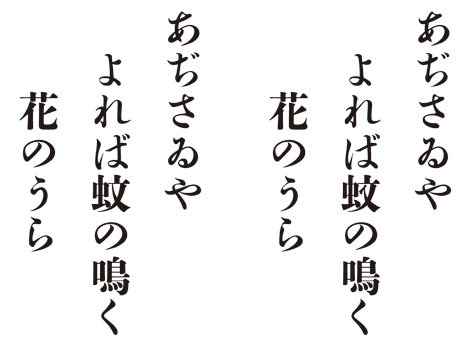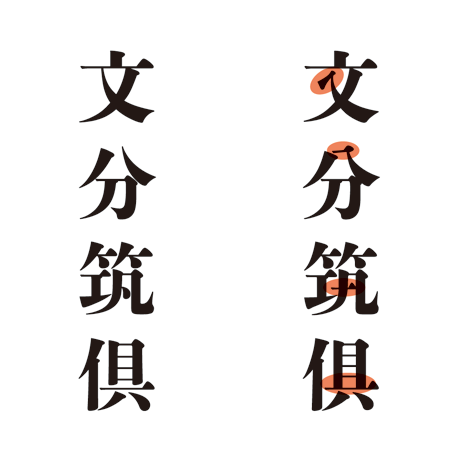
「秀英初号明朝 撰」本年9月にモリサワから発売
平成の大改刻から、初号ユーザー待望のフォントがついに登場です!
「ひっかけ」、「はちやね」や旧字形などを搭載した「秀英初号明朝 撰」を2013年9月よりモリサワから発売いたします。
(左)秀英初号明朝Std、(右)秀英初号明朝 撰
2010 年に発売した「秀英初号明朝Std」は、見出し用書体としてAdobe-Japan1-3(Std)
の文字セットに準拠しており、他の秀英体フォント製品との互換性も考慮し、Adobe-Japanの基準に沿った字形を採用しました。しかし、秀英初号明朝体の伝統的な「ひっかけ」や「はちやね」の旧字形など、"活字書体としての秀英初号明朝らしさ"を求めるユーザーからの声も多く寄せられたことから、旧字バージョンの「秀英初号明朝
撰」を開発しました。また、イタリック体や括弧なども追加収録し、見出し用書体としてより使いやすい秀英初号明朝をめざしました。
2010 年に発売した「秀英初号明朝Std」と、今回発売する「秀英初号明朝
撰」を組み合わせて使うことで、旧字と新字の両方を利用でき、より幅広い日本語表現が可能になります。
(左)秀英初号明朝Std、(右)秀英初号明朝
撰の字形の比較(上から「ひっかけ」「はちやね」「旧字形」
秀英初号明朝 撰はStdフォント(Adobe-Japan1-3準拠/9,354文字)をもと字形変更、追加収録した10,199文字となります。
今回収録する漢字は初号の開発当初から字母はできあがっていましたが、どのようにフォントとして実装するか議論を重ね、ようやくお届けできることになりました。
秀英体のフラッグシップであり和文書体の金字塔(自分で言います)、100年を経てなお愛される秀英初号明朝は、Stdと撰、ふたつそろってひとつの書体、ということで、秀英明朝ファミリーや秀英角ゴシック金&銀と丸ゴシックともども、ぜひ末永くご愛顧のほどよろしくお願いいたします。